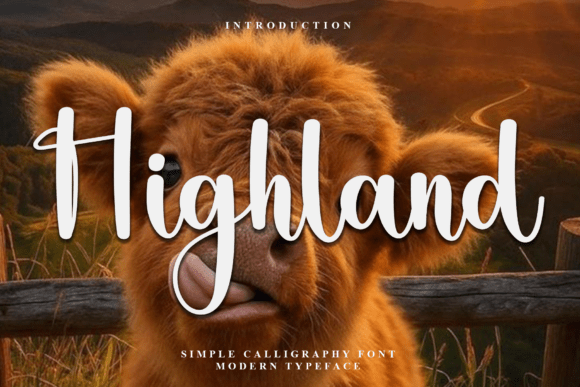
Highland
找到合适的设计元素可能具有挑战性,但 Highland 提供了一系列出色的藏品,可瞬间提升您的作品质量。
精心制作的 Highland 提供干净的矢量、流畅的排版以及让您安心的商业许可证。
无论您是创建 POD(按需打印)产品、婚礼邀请函还是社交媒体图形,Highland 都是理想的选择。